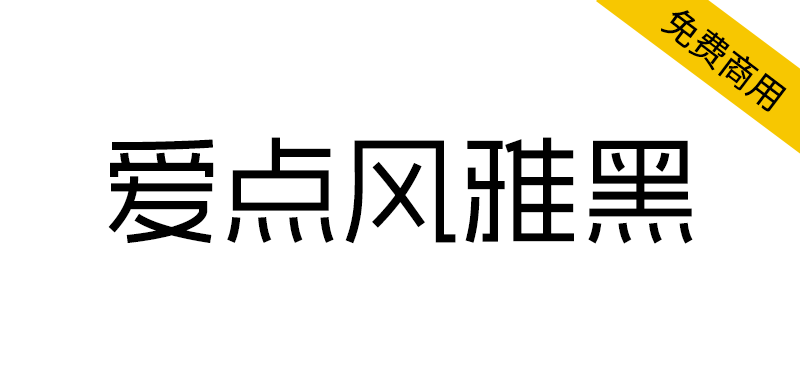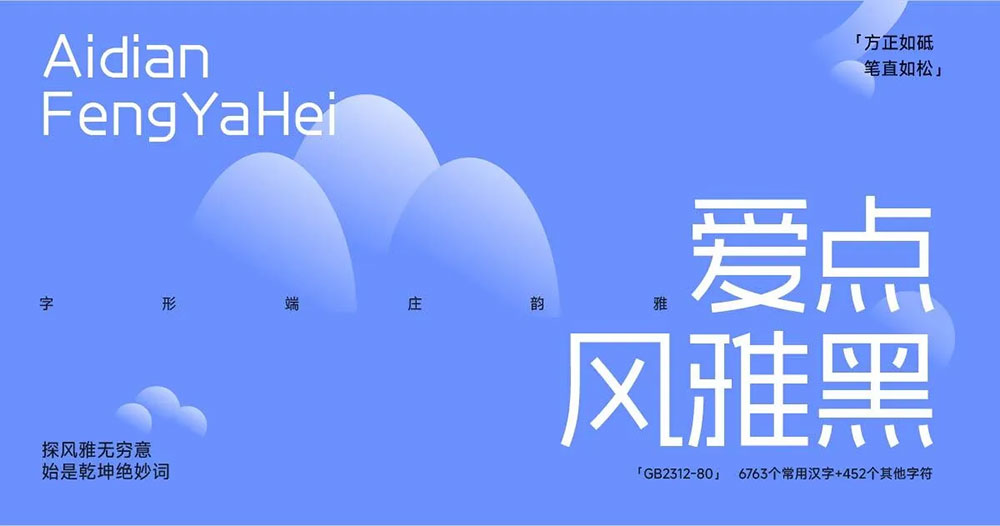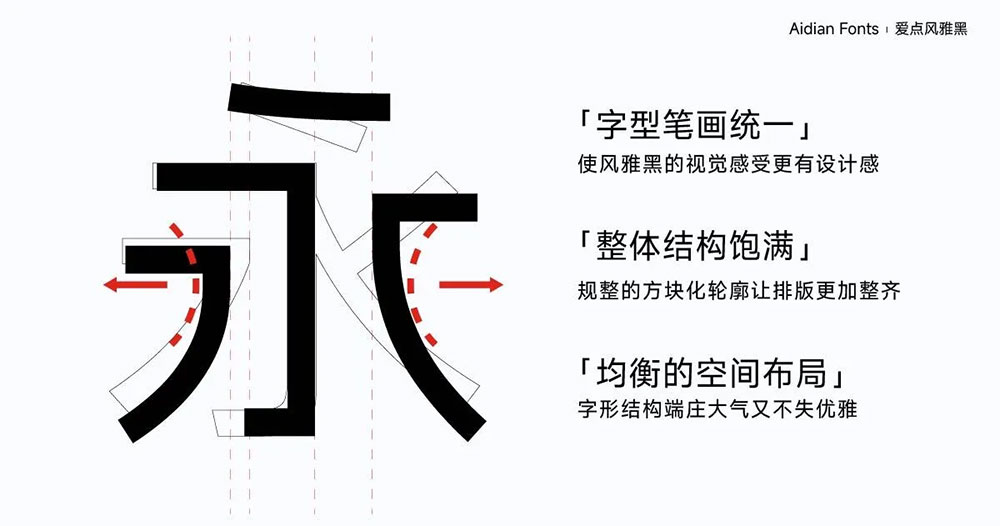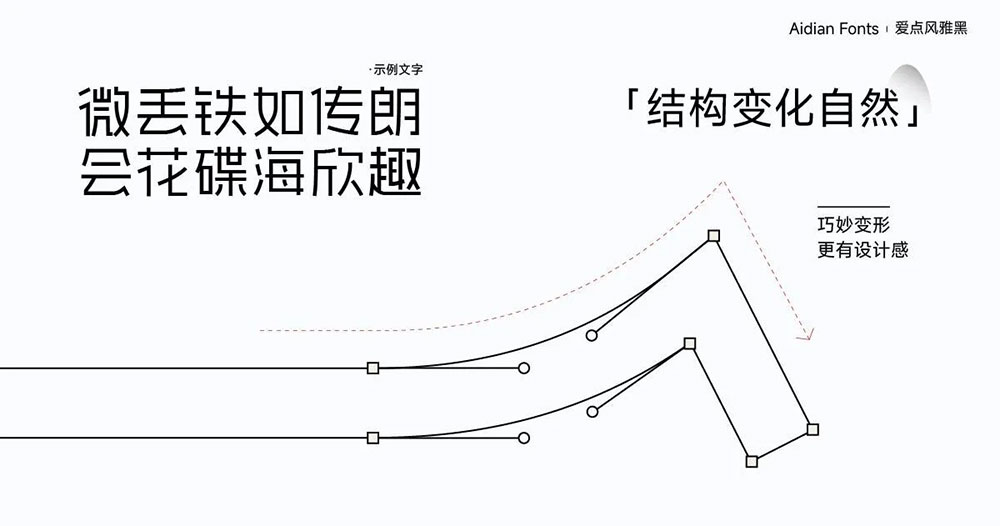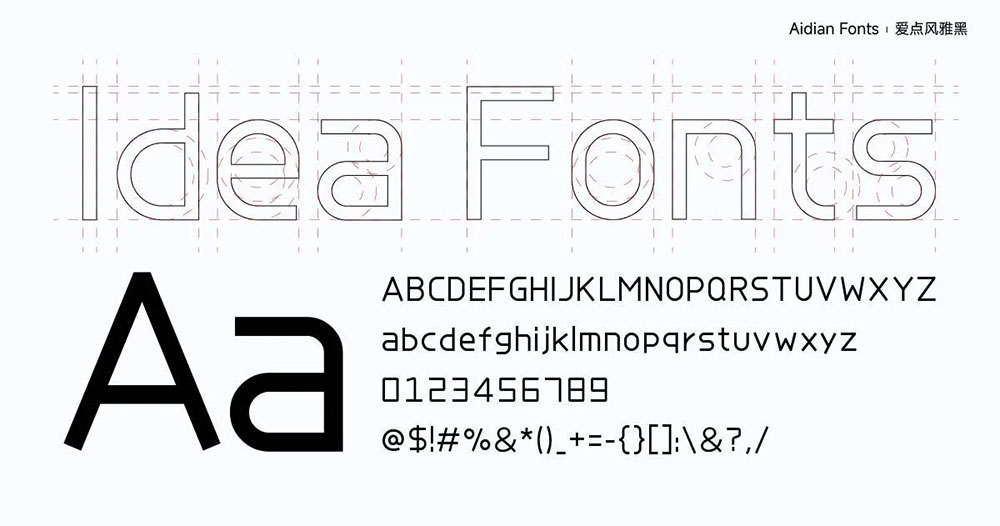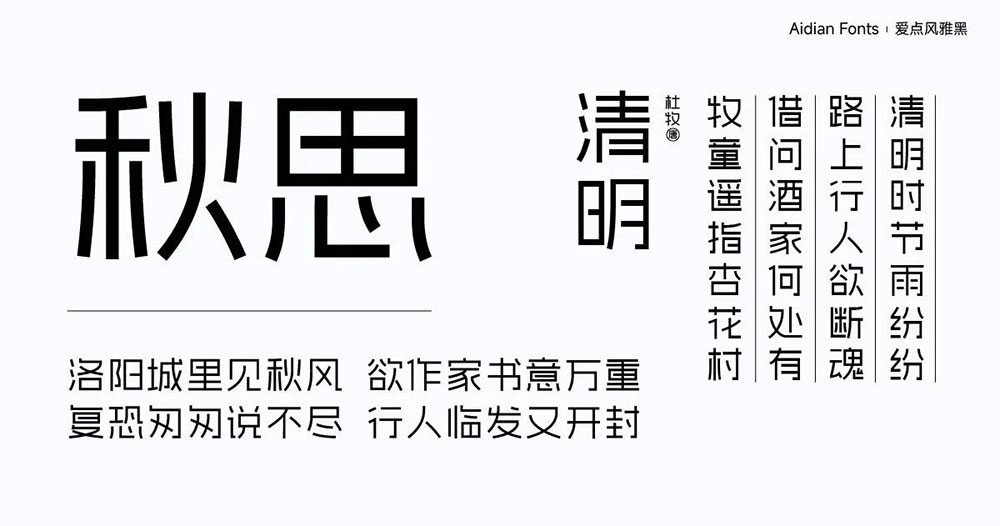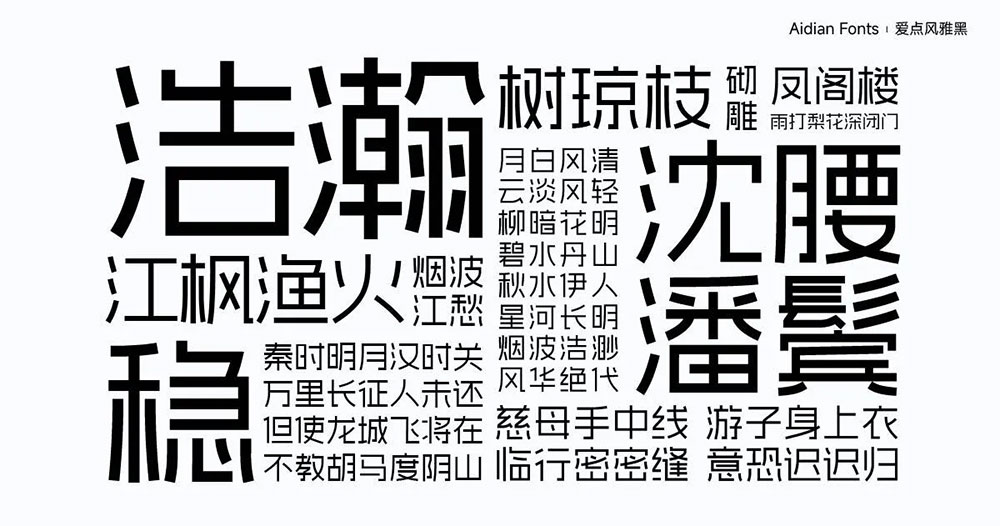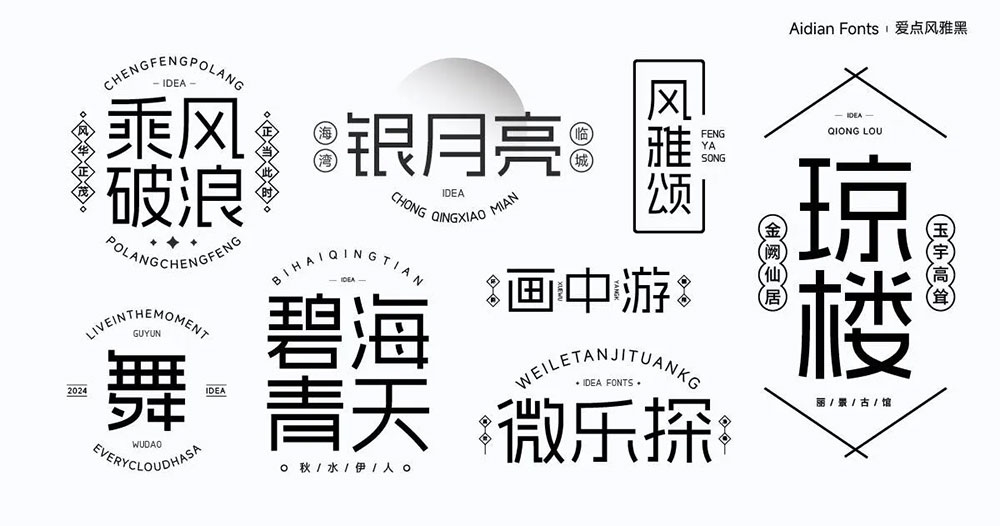
【爱点风雅黑】端正如砥、笔直如松、秀雅时尚
爱点风雅黑是广州爱点视觉文化有限公司(爱点字库)研发的商用免费字体,个人及企业可永久免费使用。该字体设计端正如砥、笔直如松,秀雅时尚,可免费用于各类广告、UI设计用途。符合GB2312-80中国国家标准汉字编码字符集标准,包含有6763个常用汉字及452个其他字符。